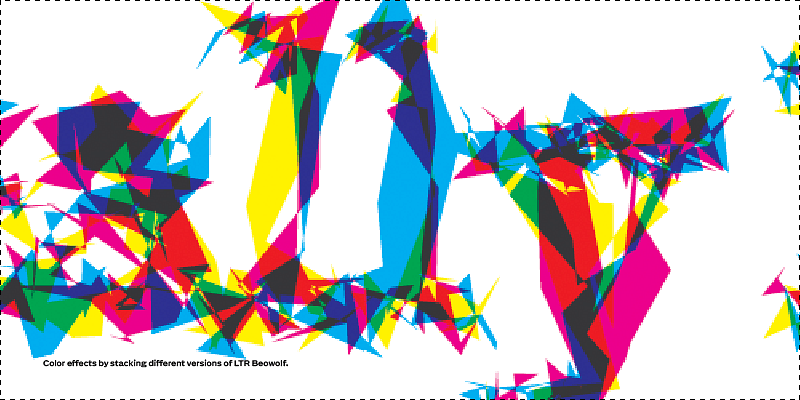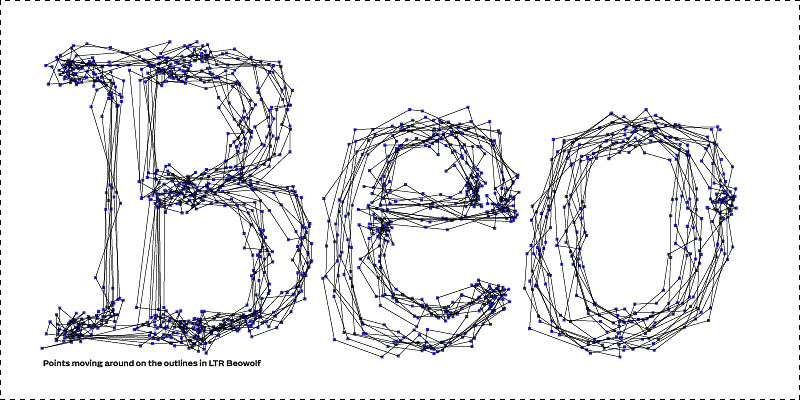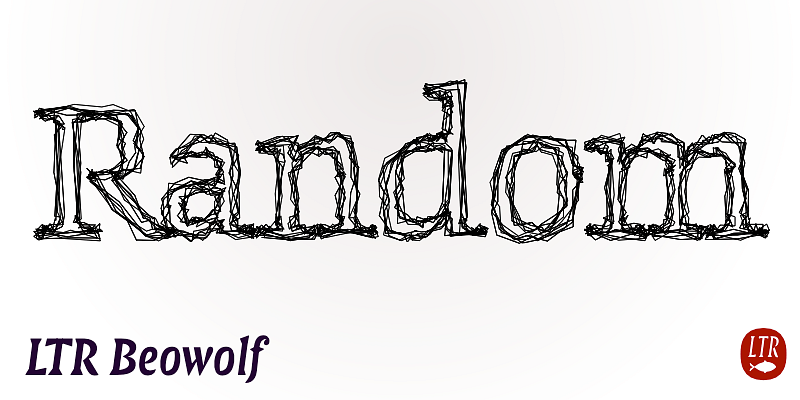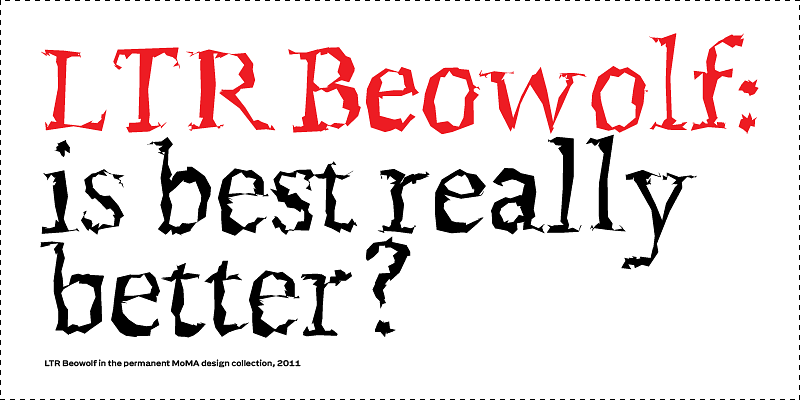
Cette édition de Beowolf est une version un peu plus sage de la Randomfont originale créée en 1989, dont les contours changeaient à chaque nouvelle impression. Les lettres passent désormais par six variantes différentes : là où l’œil humain voit du fouillis, n’importe quel périphérique de sortie voit de l’ordre. L’irrégularité est déterminée par la distance parcourue par chaque point, et il existe trois versions, de la plus raisonnable à la plus impertinente : R21, R22 et R23.
Letterror produit des conceptions novatrices depuis le début de l’ère des polices numériques. Cherchant à savoir ce qui pousse les gens à créer de telle ou telle manière et engagée dans le développement de nouveaux outils, cette entreprise a su créer un ensemble de différents travaux qui repoussent constamment les limites des polices.